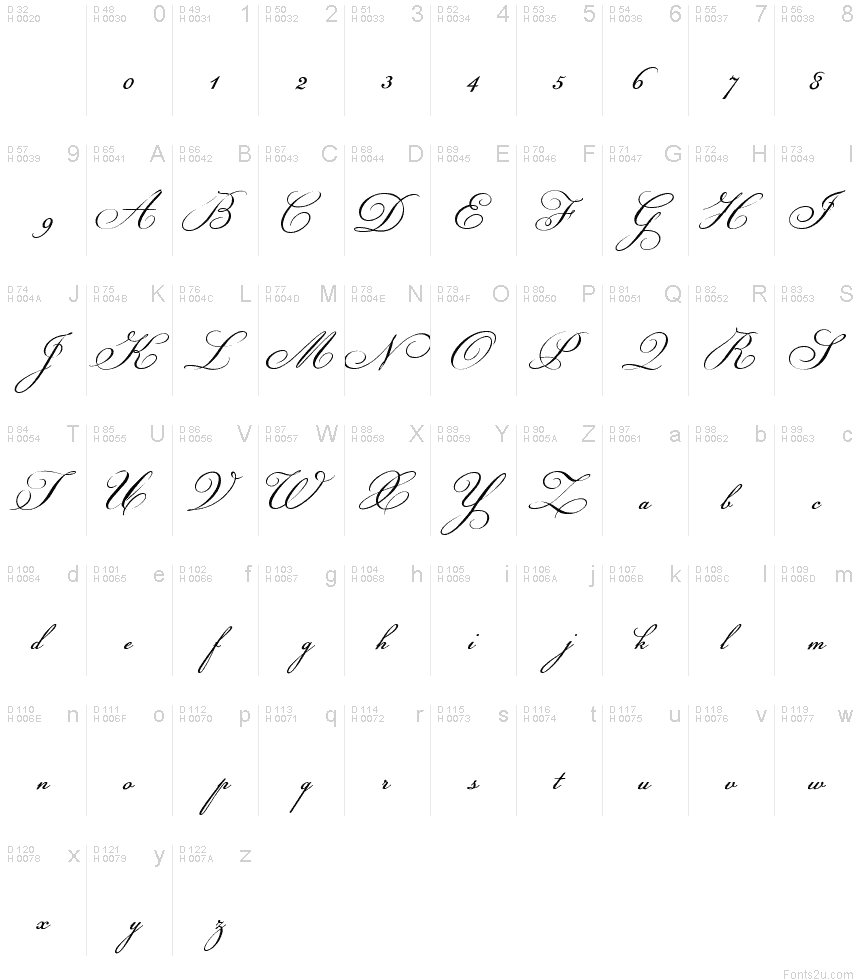
Champignon — это бесплатный каллиграфический скрипт-шрифт, передающий легкость движения стального пера по гладкой бумаге. Длинные плавные штрихи, петляющие заглавные буквы и утонченные линии напоминают надписи на бутылках шампанского — элегантно, немного театрально и очень динамично. Шрифт сохраняет отличную читаемость даже при наличии большого количества декоративных элементов, придавая вашему тексту изысканный и торжественный вид без лишней перегруженности.
Используйте Champignon для оформления свадебных приглашений, save-the-dates, изысканных меню, вывесок мероприятий, люксового брендинга, книжных обложек и романтических цитат. Этот бесплатный шрифт лучше всего смотрится в крупном кегле, позволяя его изящным изгибам «дышать», и идеально сочетается с чистым геометрическим гротеском в качестве вспомогательного шрифта для основного текста.